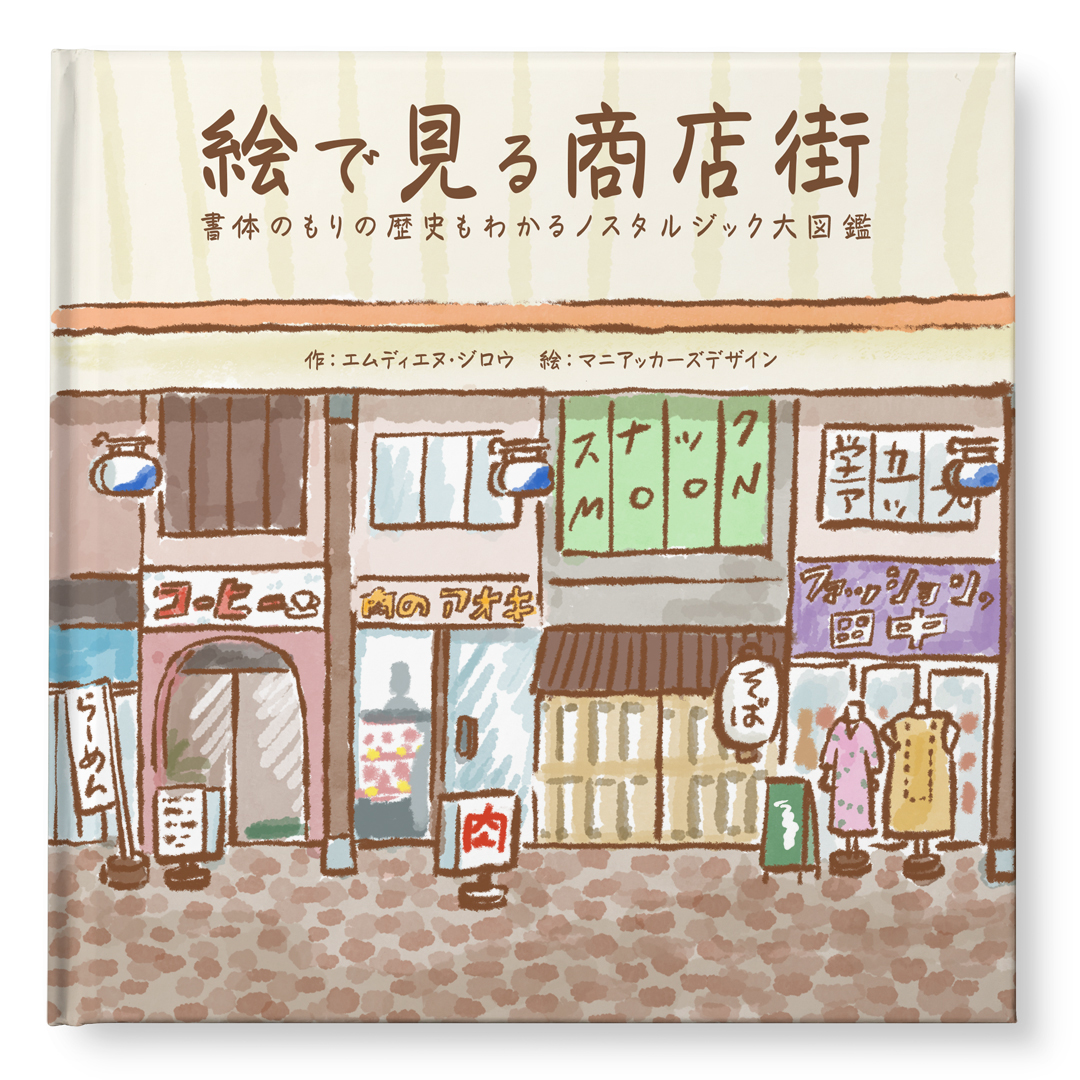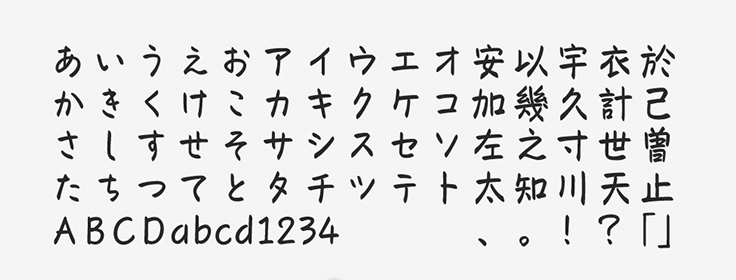
「ぺんぱる」について
ぺんぱるは2020年の新書体としてリリースされたフォントです。本来、手書き風の書体は実際に書いた文字をスキャンしてベースとしてデザインが進められることも多いのですが、ぺんぱるは全てデジタル上で作られました。手書き調ではあるものの安定した骨格を持ち、読みやすさに定評のあるフォントです。
「ぺんぱる」の特徴
フェルトペンでラフに手書きしたようなフォントで、親しみやすい雰囲気を備えています。フリーハンドならではの運筆が特徴的で、自然な印象に見えやすいフォントです。メモ書きのようなスピード感や肉声もイメージさせるフォントと言えるでしょう。
ぺんぱるは温かみのある日常を感じさせるようなシーンには特にマッチしやすく、デザインを身近なものへと演出できる力を備えています。かっちりとはしすぎず、それでいて雑ではなく、絶妙なバランスが保たれたデザインです。
作例は商店街の歴史を題材とした絵本の表紙で、素朴なタッチのイラストにぺんぱるの文字を組み合わせて優しい温かみを表現しています。ぺんぱるは読者に親しみやすさを感じてもらうためにはとても効果的なフォントです。
「ぺんぱる」の書体情報